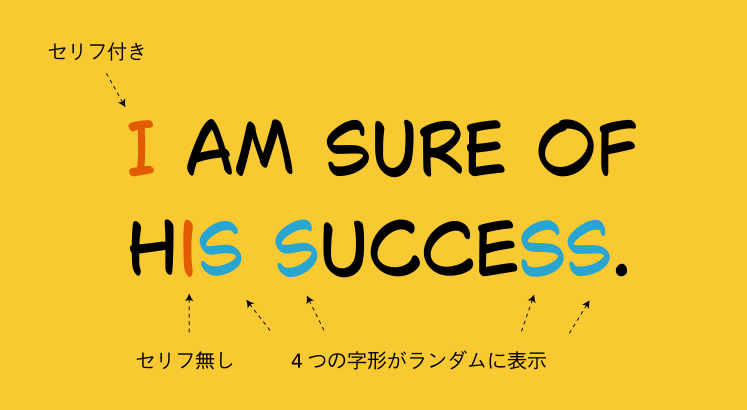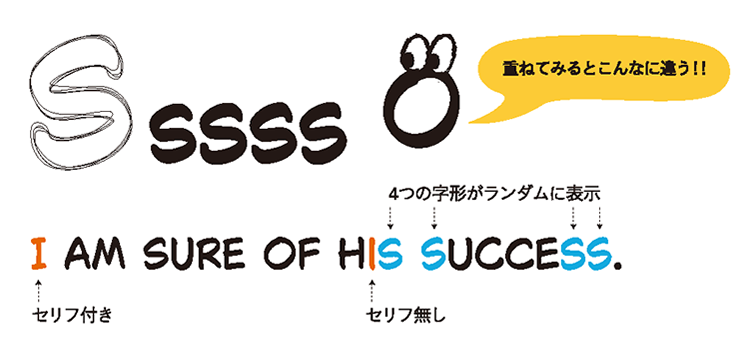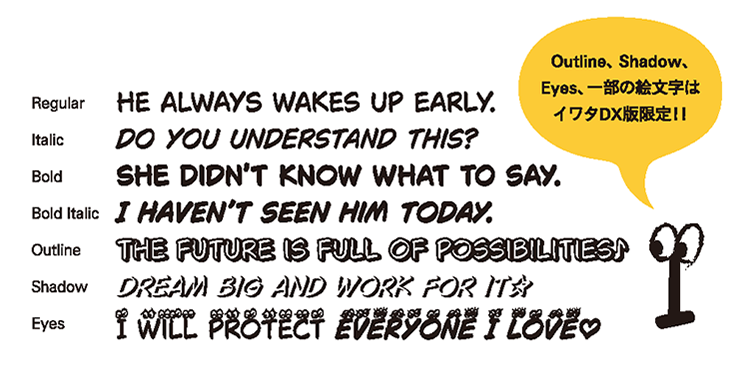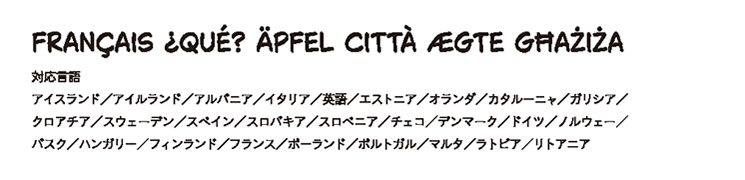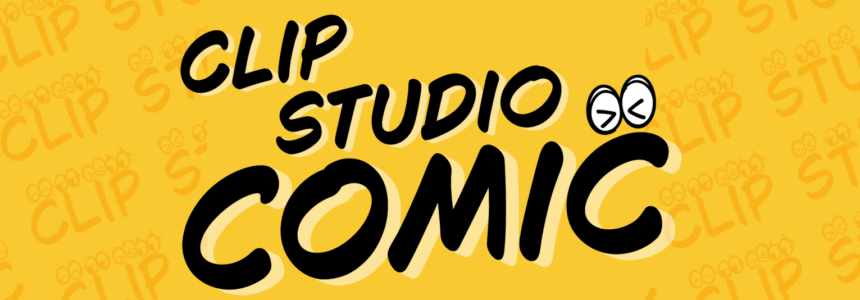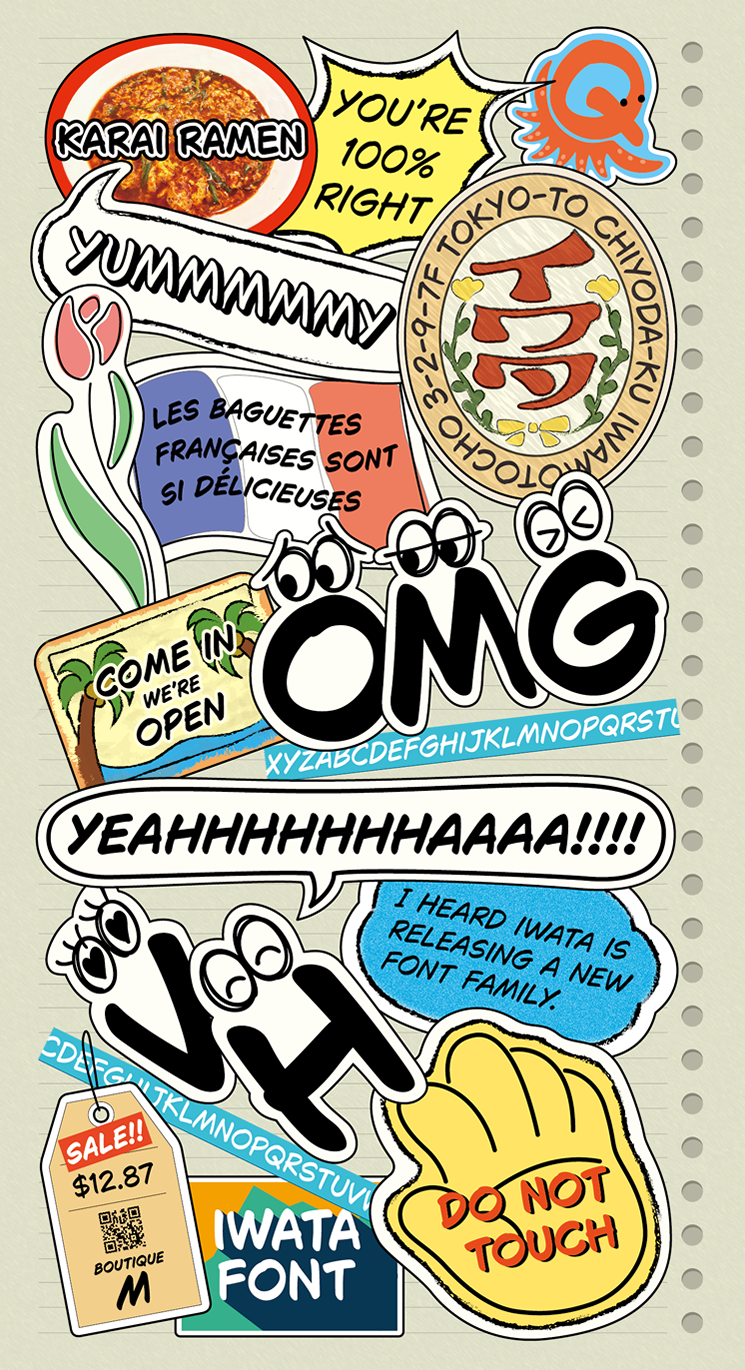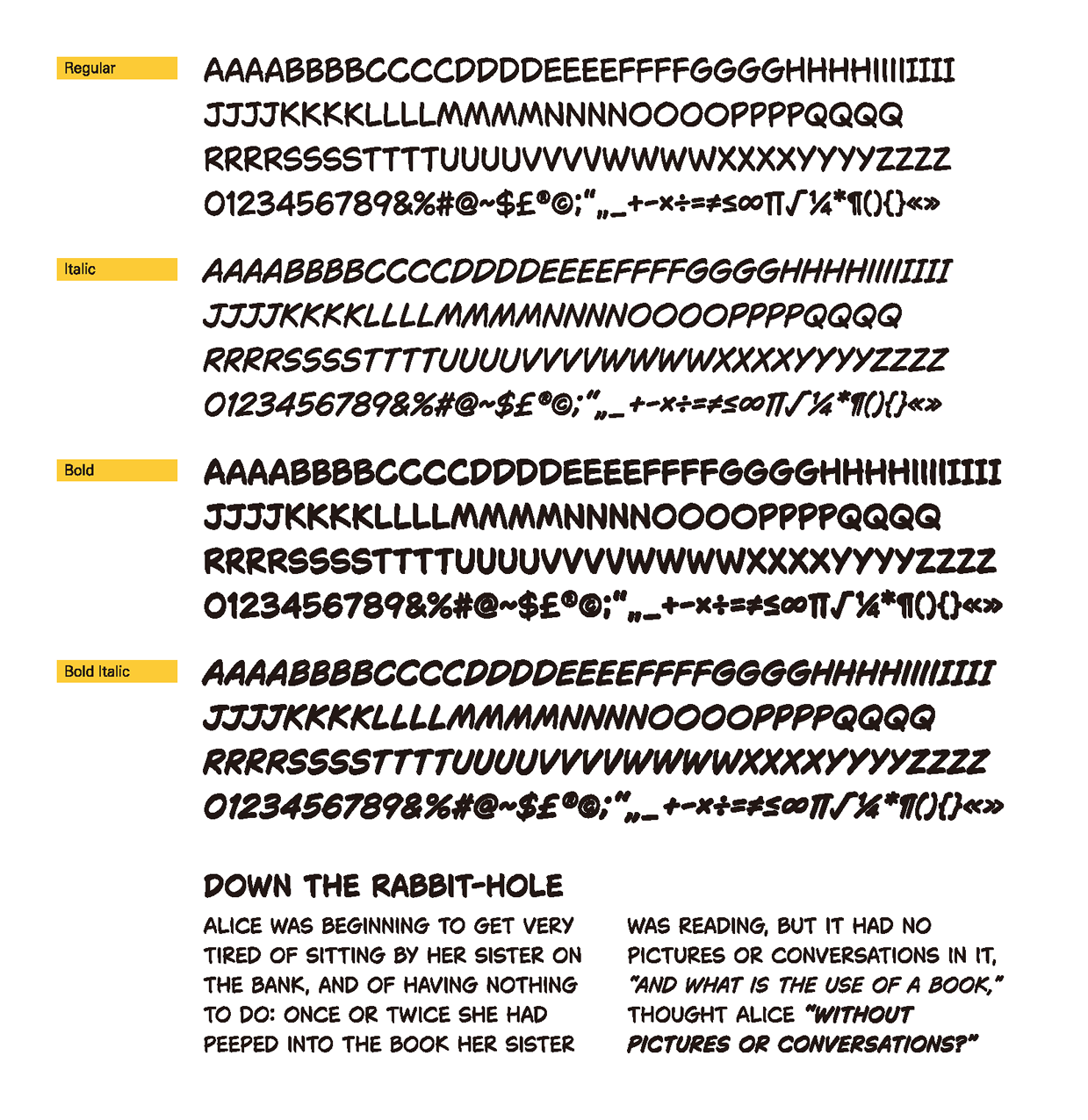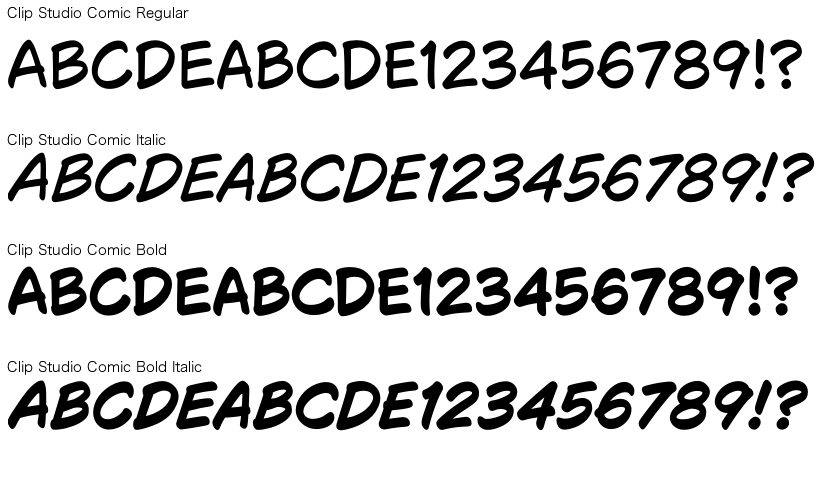
まるで手書き!?CLIP STUDIO PAINT専用フォント Clip Studio Comic(イワタフォント)
〜CLIP STUDIOで使える、漫画表現のためのフォントセット〜
イラスト・マンガ・Webtoon・アニメーション制作のアプリ「CLIP STUDIO PAINT」の専用欧文フォント
『Clip Studio Comic』がイワタとセルシスで共同開発されました。
■ まるで手書き!?
文字それぞれに4つの字形を収録。
入力するたびにランダム表示され、まるで手書きのような組版を実現。
ネイティブユーザーからの希望が多かった、一人称の「I」に自動でセリフが付く機能を搭載されています。
一人称の時にセリフ(髭)がつくことで、実際に書くときのイメージが表現できます。
■ 使い方は無限大!
「Clip Studio Paint Ver.3.0」移行標準搭載版とイワタDX版をご用意。
イワタDX版は追加絵文字やOutlineなどのバリエーションが仲間入りしてパワーアップ。
組み合わせて使うことで表現の幅がさらに広がります。
■ 多言語に対応!
フランス語、スペイン語、ドイツ語、イタリア語などラテンアルファベット圏の多くの言語をカバー。
Clip Studio Comic Regular/Italic/Bold/Bold Italic
■Clip Studio Comic『イワタDX 版』
Iwata Clip Studio Comic Regular/Italic/Bold/Bold Italic
Iwata Clip Studio Comic Outline Regular/Italic/Bold/Bold Italic
Iwata Clip Studio Comic Shadow Regular/Italic/Bold/Bold Italic
Iwata Clip Studio Comic Eyes Regular/Italic/Bold/Bold Italic